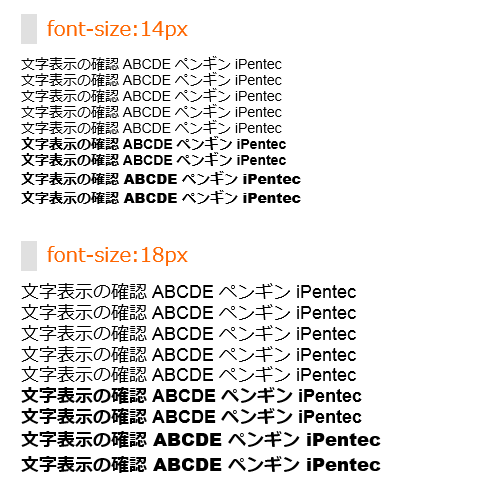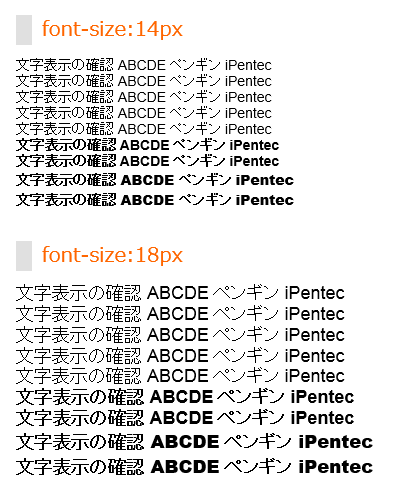
Internet Explorer 11 (Windows 8.1) で以前のバージョンとフォントが異なる
Internet Explorer 11 (Windows 8.1) にバージョンアップするとWebブラウザでページを表示した際の字体が以前のバージョンと違って見える場合があります。
原因
font-familyの"sans-serif"に対応するフォントに変更が加えられた模様です。
変更点
Internet Explorer 10 以前
font-family:sans-serif;
を指定した場合、日本語フォントには"MSゴシック"が適用されます。
Internet Explorer 11
font-family:sans-serif;
を指定した場合、日本語フォントには"メイリオ"が適用されます。
表示の違い
スタイルに"font-family:Arial,sans-serif;"を指定した文字をInternet Explorer 10とInternet Explorer 11で比較します。(上からfont-weightを100づつ増やしています。)
• Internet Explorer 10
Internet Explorer 11 (Windows 8.1) で以前のバージョンとフォントが異なる:画像1
• Internet Explorer 11
Internet Explorer 11 (Windows 8.1) で以前のバージョンとフォントが異なる:画像2
日本語のボールド書体の文字で大きな違いが出ます。
対策
以下の対策があります。
font-familyに "sans-serif"を指定せず、"Arial"のみを指定
font-familyにsans-serifを指定せず、Arialのみを指定すると違いがなくなります。
スタイルに"font-family:Arial;"を指定した文字をInternet Explorer 10とInternet Explorer 11で比較します。
表示の違いがほとんどなくなりました。
• Internet Explorer 10
Internet Explorer 11 (Windows 8.1) で以前のバージョンとフォントが異なる:画像3
• Internet Explorer 11
Internet Explorer 11 (Windows 8.1) で以前のバージョンとフォントが異なる:画像4
font-familyにフォント名"MSゴシック"を記述する
font-familyに直接フォント名を指定することで、同じフォントを利用させることができます。